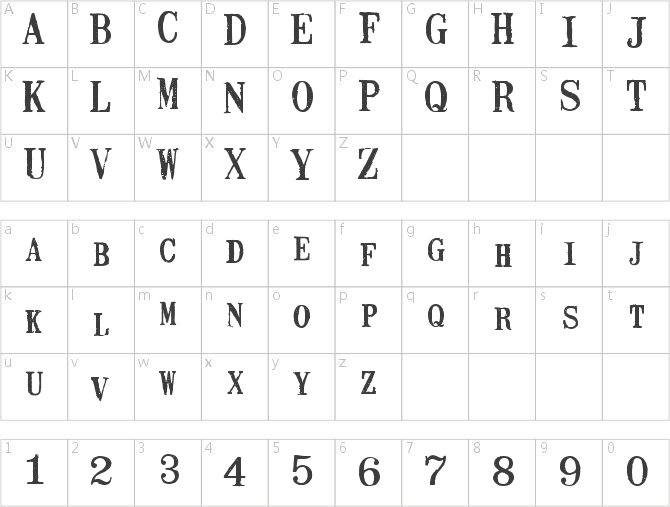
MailartRubberstamp-Regular 詳情頁
MailartRubberstamp-Regular字體字庫是一款讓人賞心悅目、百看不厭的英文字體,適合各類廣告和產(chǎn)品包裝設(shè)計應(yīng)用,字體大小0.83MB,格式為ttf字體,上傳用戶是我,Dirac,作者/版權(quán)方為未知